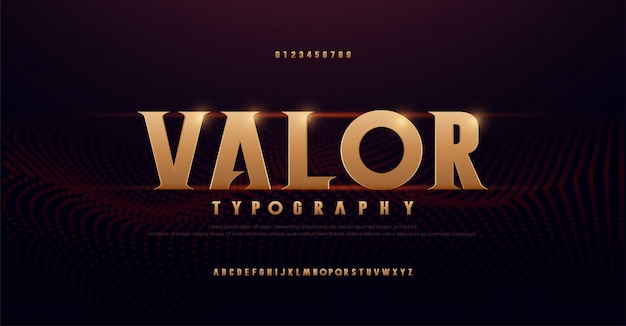
Polices Abstraites Alphabet Or Serif. Typographie Moderne Doré Pour Le Rock, La Musique, Le Jeu, L'avenir, La Création, La Police De Conception De Polices 3d Et Le Nombre. Vecteur Premium